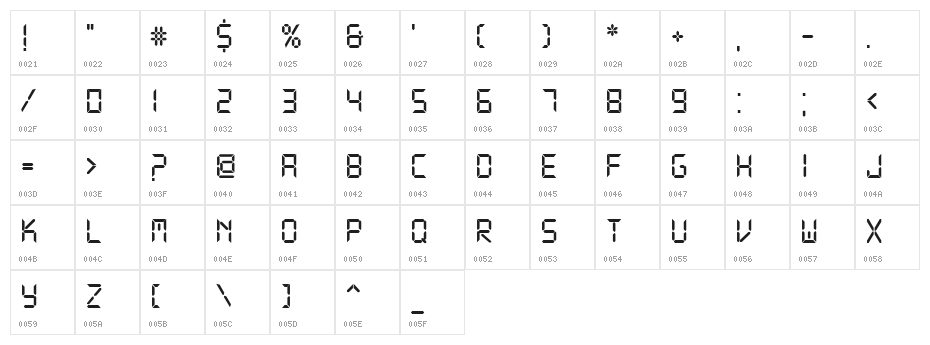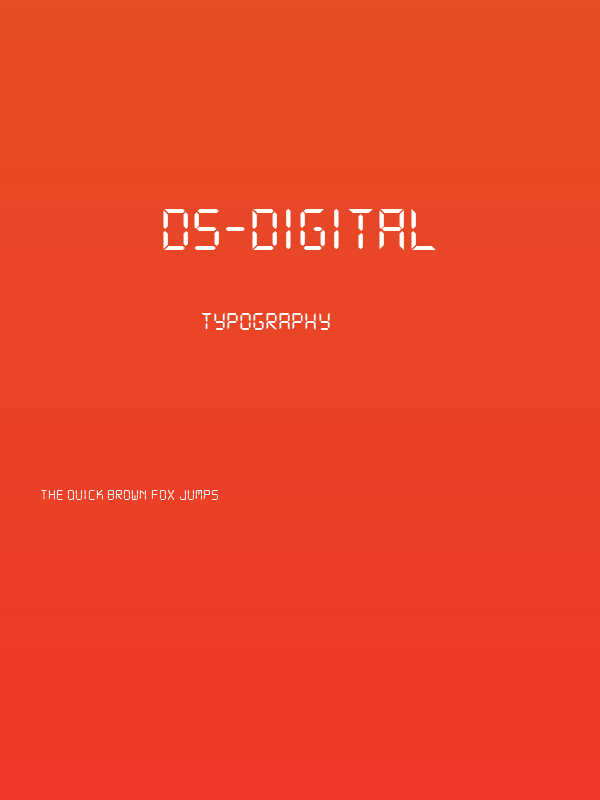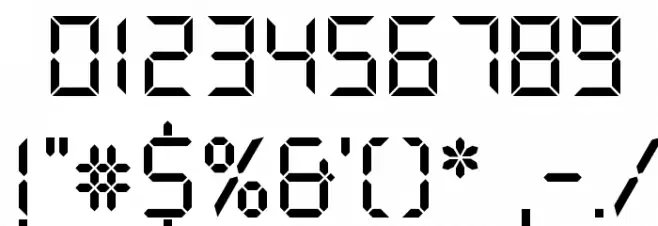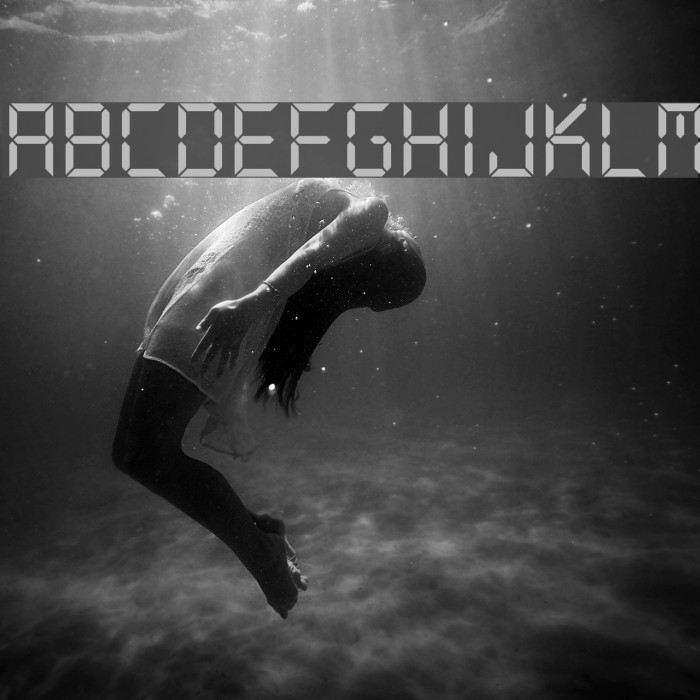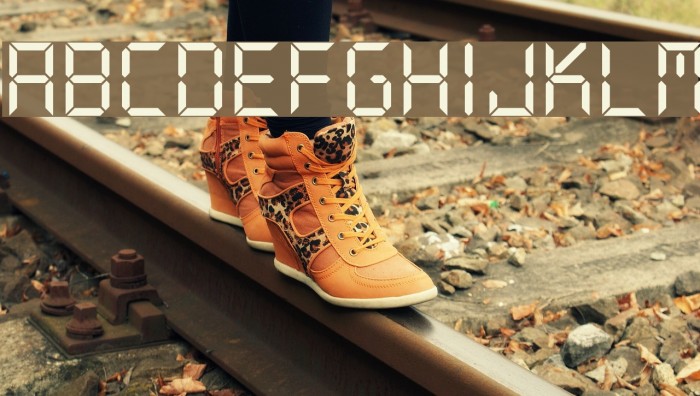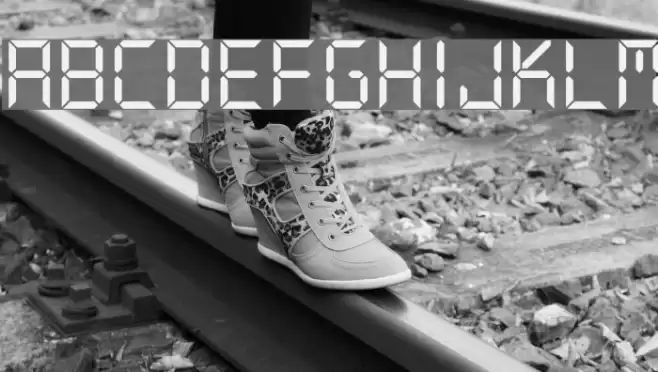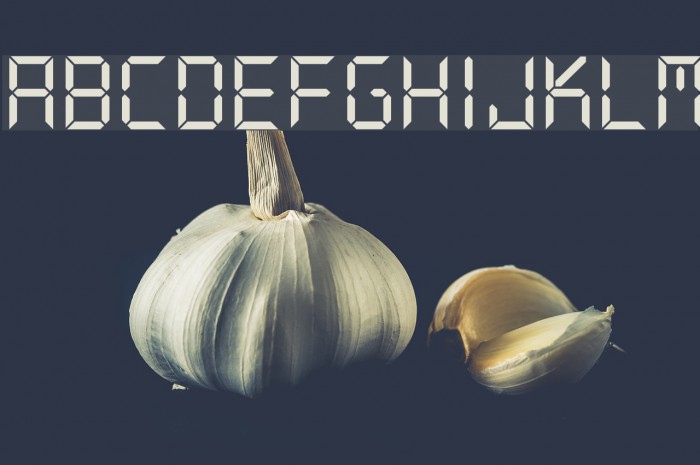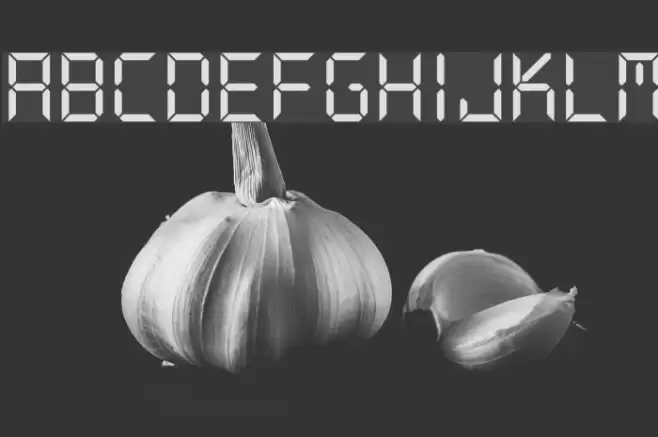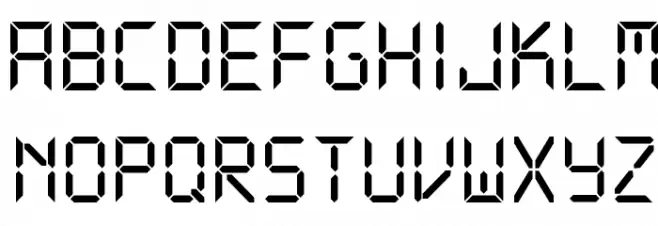
DS-Digital Font
| Cas d'utilisation | Headlines, Logos, Digital displays |
| Projets proposés | Ideal for digital clocks, tech-themed designs, retro gaming interfaces, and electronic device displays. |